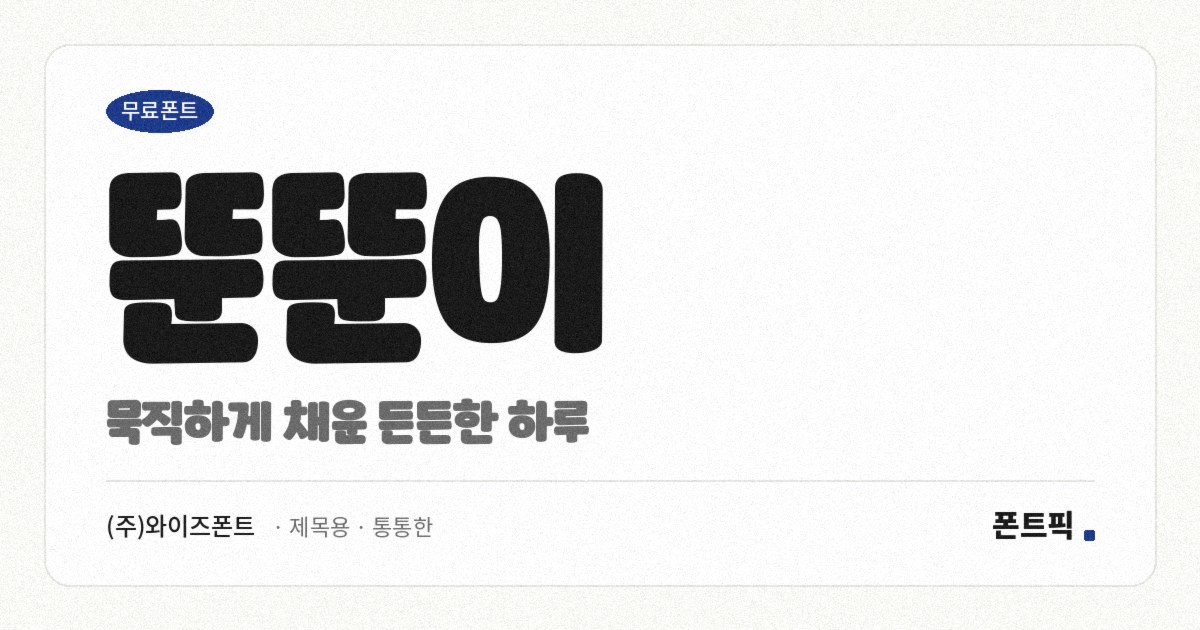
뚠뚠이
TDTDTuntuni
- 분류제목용 · 통통한
와이즈폰트가 2020년에 내놓은 손글씨 서체입니다. 제작사는 이 서체를 동글통통 귀여운 손글씨 폰트라고 소개하면서 제목용과 자막용으로 잘 어울린다고 밝혔습니다.
파일을 열어 재어 보면 그 설명이 맞습니다. 획이 굵고 속이 꽉 차서 자면을 채우는 비율이 0.46에 이릅니다. 폰트픽에 올라온 같은 굵기의 한글 서체 138종 가운데 열 번째로 진한 축입니다. 낱자는 높이보다 폭이 넓어 가로로 퍼져 있고, 받침이 붙어도 글자 높이가 거의 변하지 않는 네모틀이라 굵은 획에도 글줄이 흐트러지지 않습니다.
한 가지 미리 확인하실 것이 있습니다. 이 서체의 한글은 2,574자입니다. 완성형 11,172자를 다 담은 것이 아니라 흔히 쓰는 글자 위주로 골라 넣은 것이라 드문 음절이 들어가면 네모로 빠집니다. 정해진 문구를 조판할 때는 문제가 없지만 이름이나 주소처럼 어떤 글자가 올지 모르는 자리에는 미리 확인하고 쓰세요. 굵기는 하나입니다.